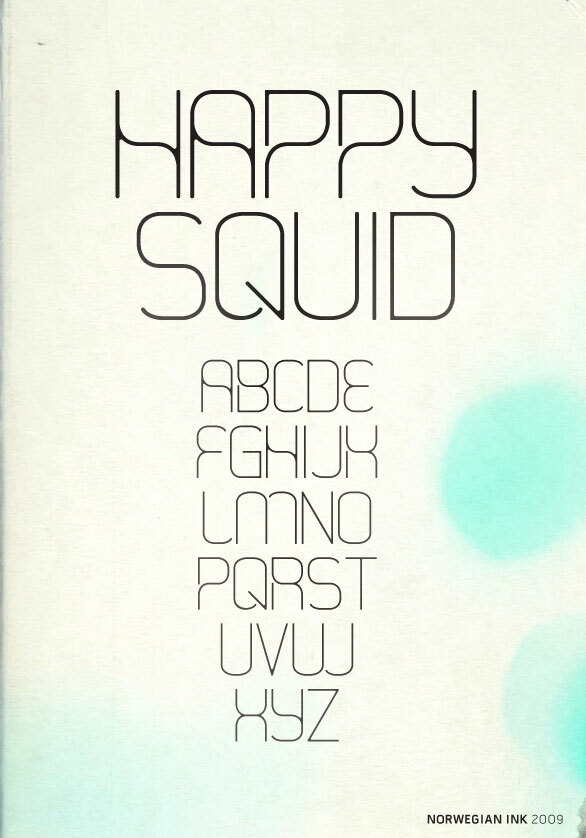
Happy Squid è un carattere display monolineare gratuito, composto da tratti sottili e continui. Curve arrotondate e raccordi aperti donano alle lettere una struttura geometrica pulita con una morbidezza inaspettata. Il tratto si mantiene arioso e preciso in ogni dettaglio.
Sia il branding per il settore tecnologico sia l'editoria per l'infanzia possono sfruttare la sua struttura semplice e amichevole, sebbene per pubblici molto diversi. È ideale anche per manifesti di eventi e packaging contemporanei, dove gli angoli fluidi possono richiamare cavi, percorsi o profili disegnati, diventando parte integrante dell'illustrazione circostante.
Happy Squid
Disegnato da Frode Nordb